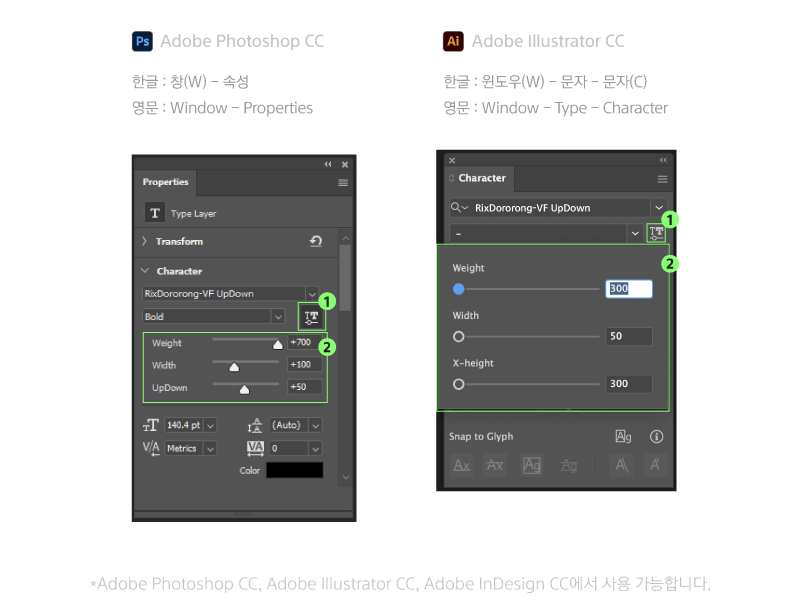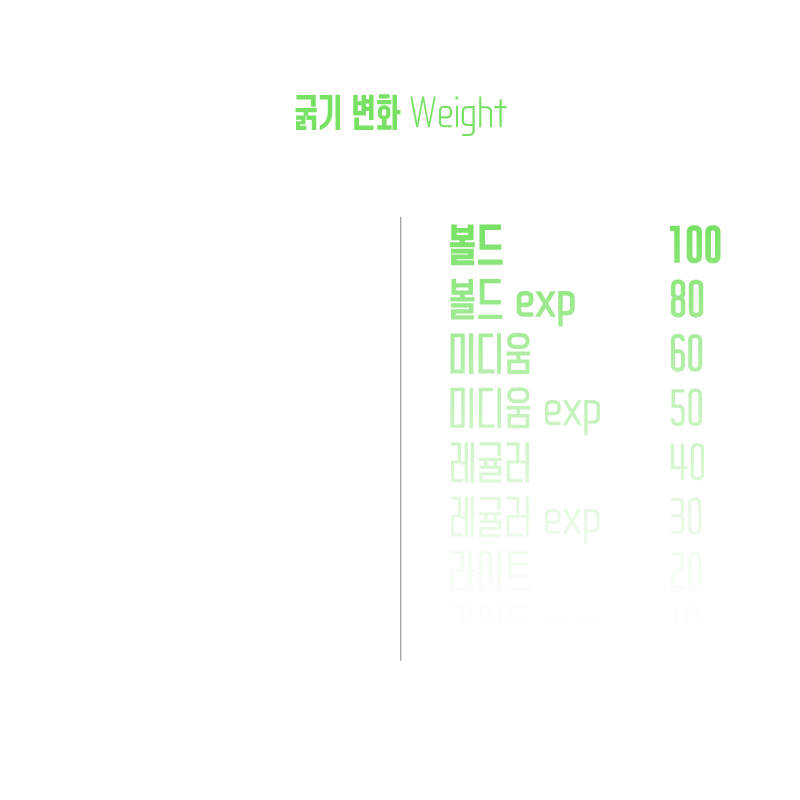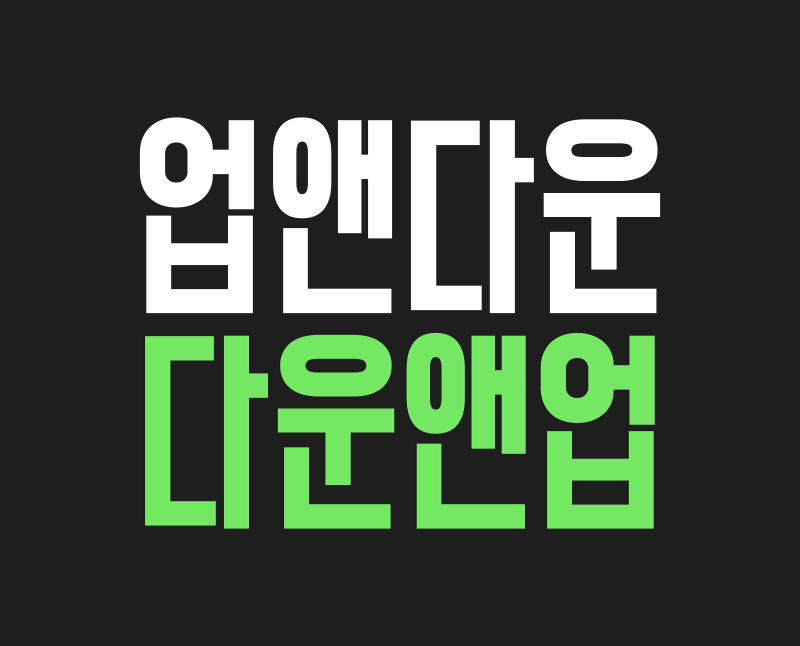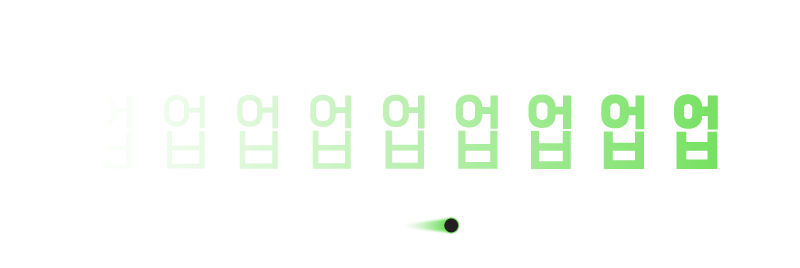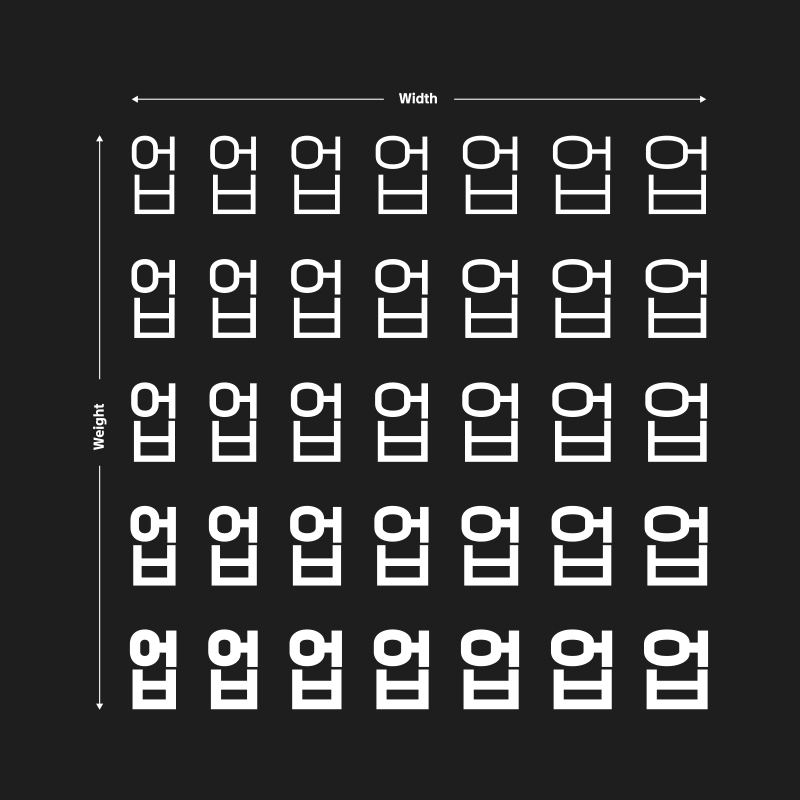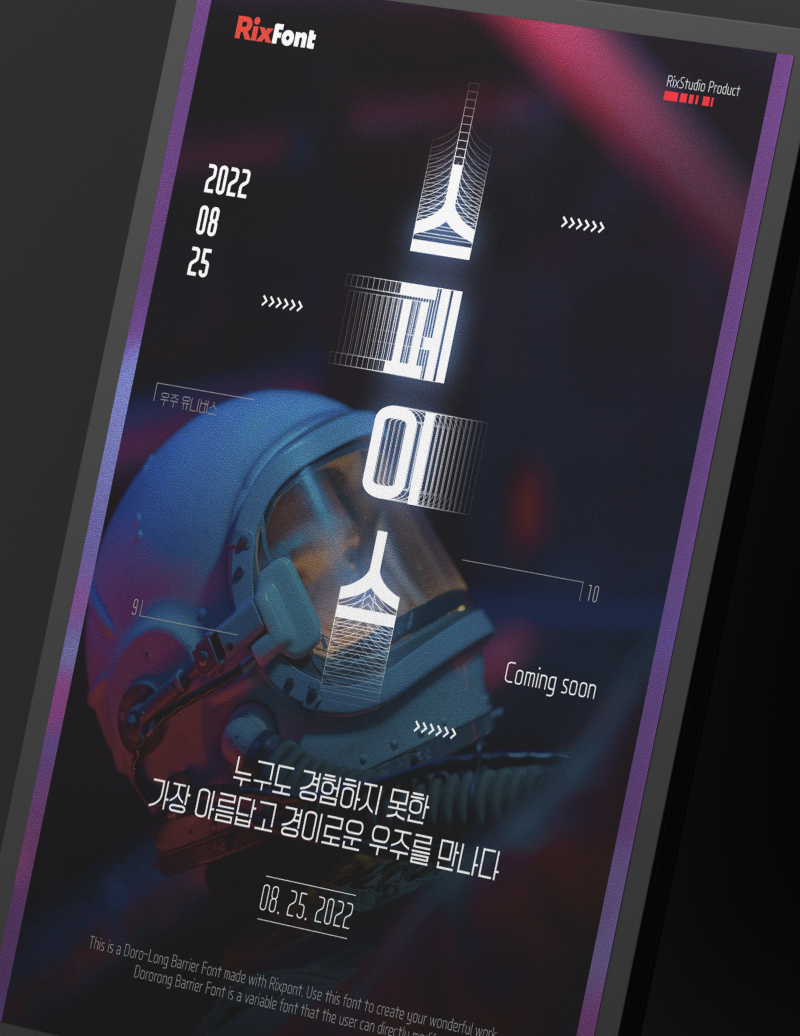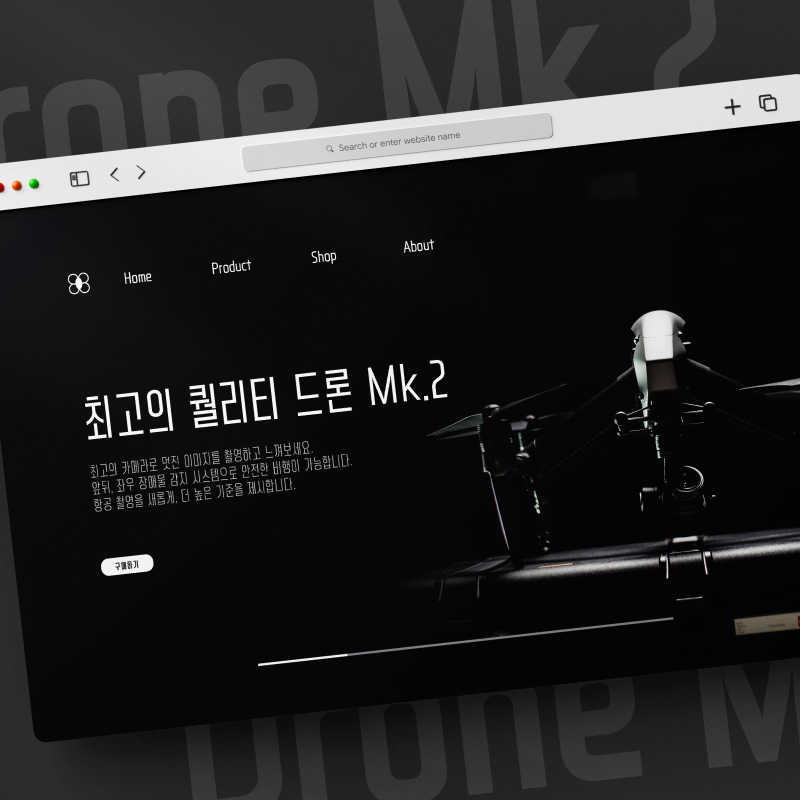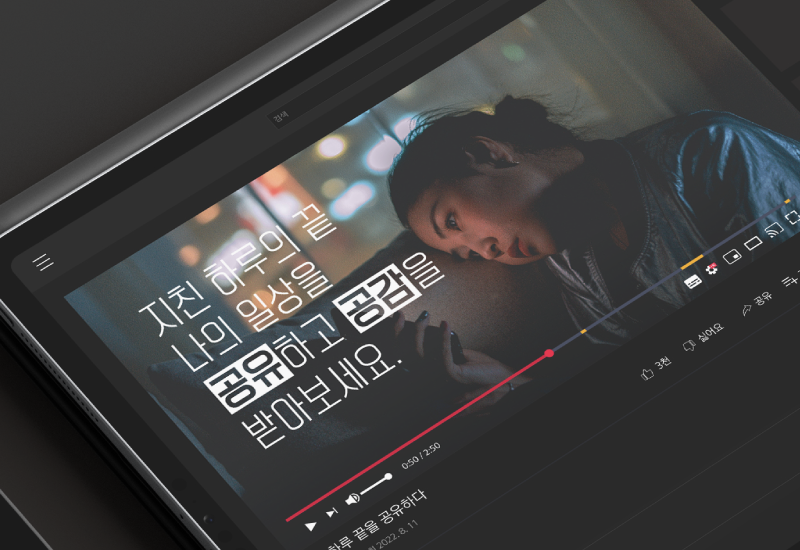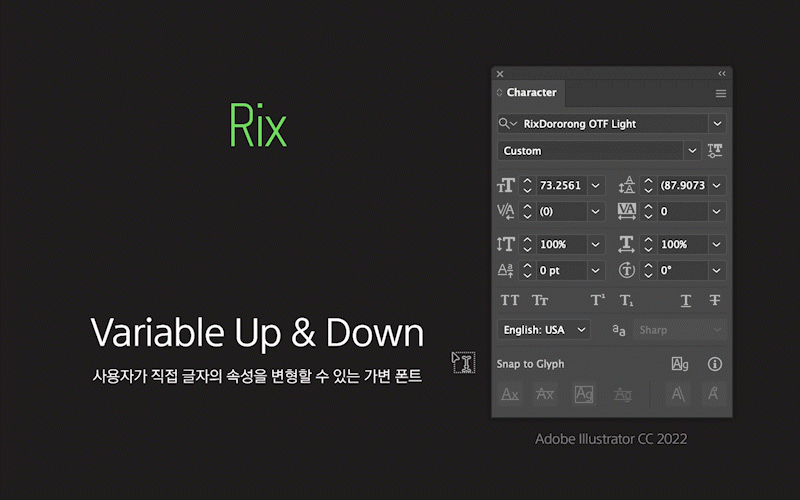
RixDororong-VF-UpDown
폭이 좁고 깔끔한 인상의 Rix도로롱 서체를 기반으로 제작한 배리어블 폰트입니다.
글자의 굵기, 무게 중심, 너비를 사용자가 직접 조절해 변형할 수 있습니다.
양 극단의 특징들을 혼합 전개하여 하나의 폰트로 다양한 표현이 가능합니다.
배리어블 폰트란, 글자 굵기, 너비 등 사용자가 직접 변형할 수 있는 서체입니다.
도로롱배리어블 UpDown은 Light부터 Bold까지
굵기를 자유롭게 표현할 수 있습니다.
글자의 무게 중심과 너비를 사용자가 직접 설정해 다양한 변주를 줄 수 있습니다.